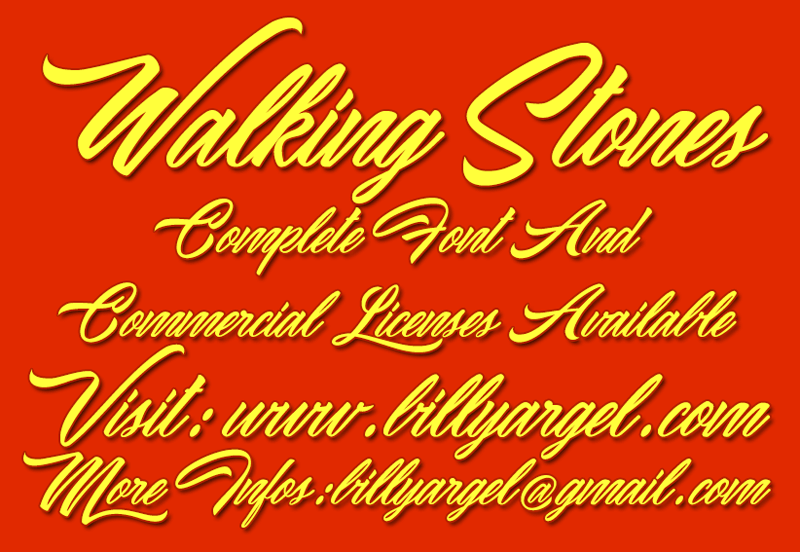
Walking Stones Font – Download Grátis
A Walking Stones Font é uma elegante escolha para quem busca uma escrita agradável e autêntica. Esta fonte handwritten vem diretamente do talentoso designer Billy Argel, disponível gratuitamente para uso pessoal. Com um estilo natural e fluido, essa fonte é perfeita para gráficos de newsletter, cartões de aniversário ou outros projetos digitais onde uma escrita artesanal seja bem-vinda. Através do site oficial de Billy Argel, você pode obter licenças comerciais e um conjunto completo da fonte. Além disso, visitar o site principal ou dar uma olhada no Facebook oficial dos seus projetos adicionará mais valor ao seu conhecimento sobre a Walking Stones Font. Como designer de fontes autêntico e apaixonado, Billy Argel oferece um serviço atento aos clientes para qualquer dúvida ou necessidade adicional que você possa ter. A Walking Stones Font é uma ótima escolha para quem procura uma escrita elegante e natural em seu design digital. Suas linhas suaves e texturas variadas criam um efeito único, tornando-a perfeita para trabalhos de arte gráfica e ilustração. Compreender as vantagens desse conjunto completo e adquirir a licença comercial garantirá que você possa usar com mais frequência e em diferentes ambientes, desde seu site pessoal até um projeto empresarial.
Designer: Billy Argel